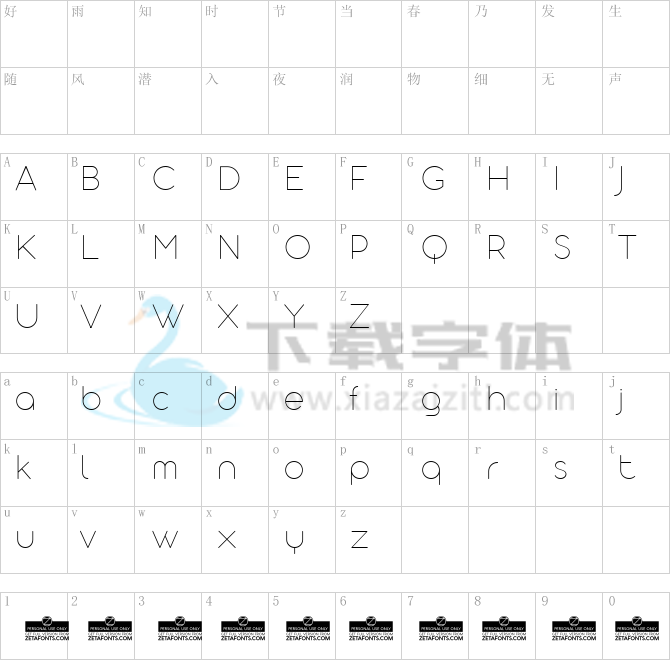
Aristotelica Display Trial.ttf字体下载,这款字体结构工整、笔画清晰,兼顾美观与易读性,适用于标题、正文、海报、包装、LOGO 等多种场景。字形优雅稳定,风格百搭耐看,适配日常排版与创意设计,让文字呈现更舒适、更具质感。Aristotelica Display Trial.ttf字体下载一笔一画,皆是细节,以均衡的比例、流畅的线条打造舒适视觉体验,字形端正大气,风格简约现代。无论是商业设计、品牌宣传还是日常排版,都能轻松驾驭,让文字更有格调与力量。Aristotelica Display Trial.ttf字体下载字体下载。